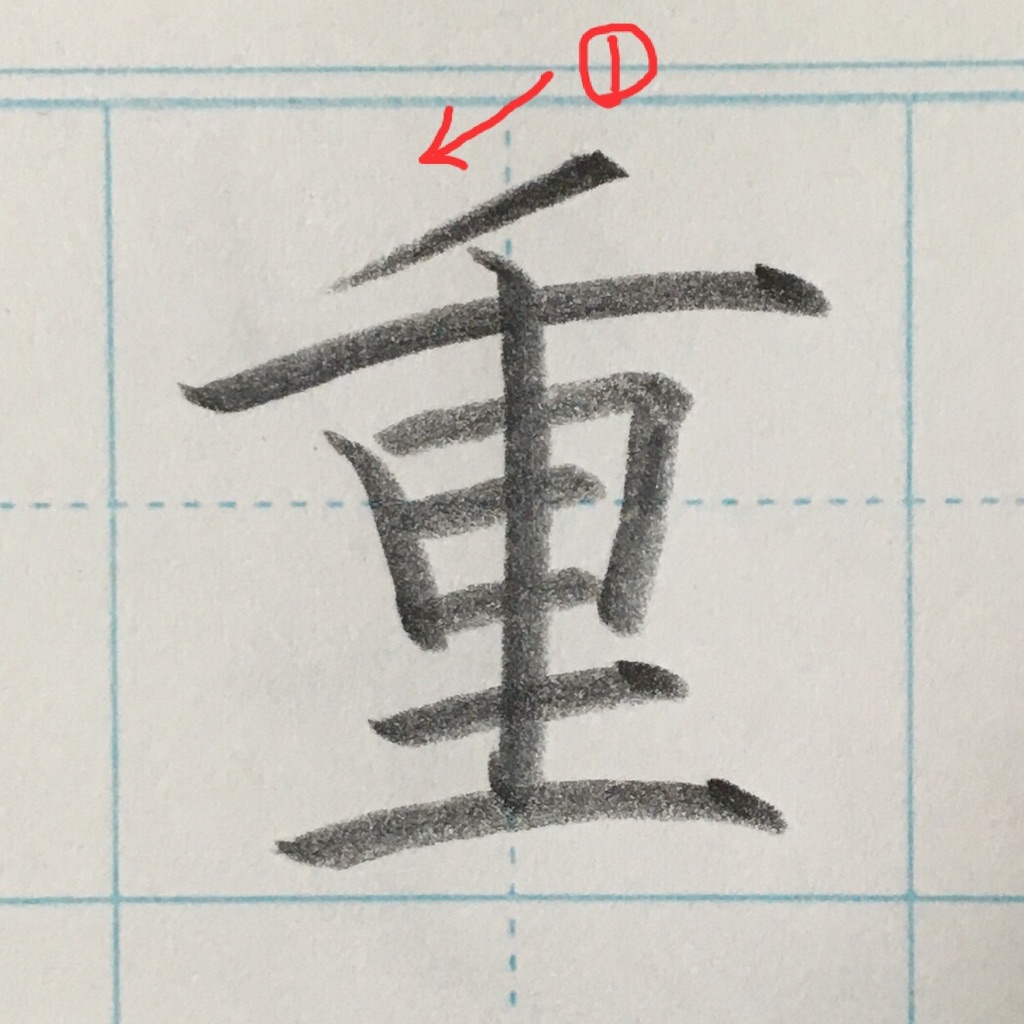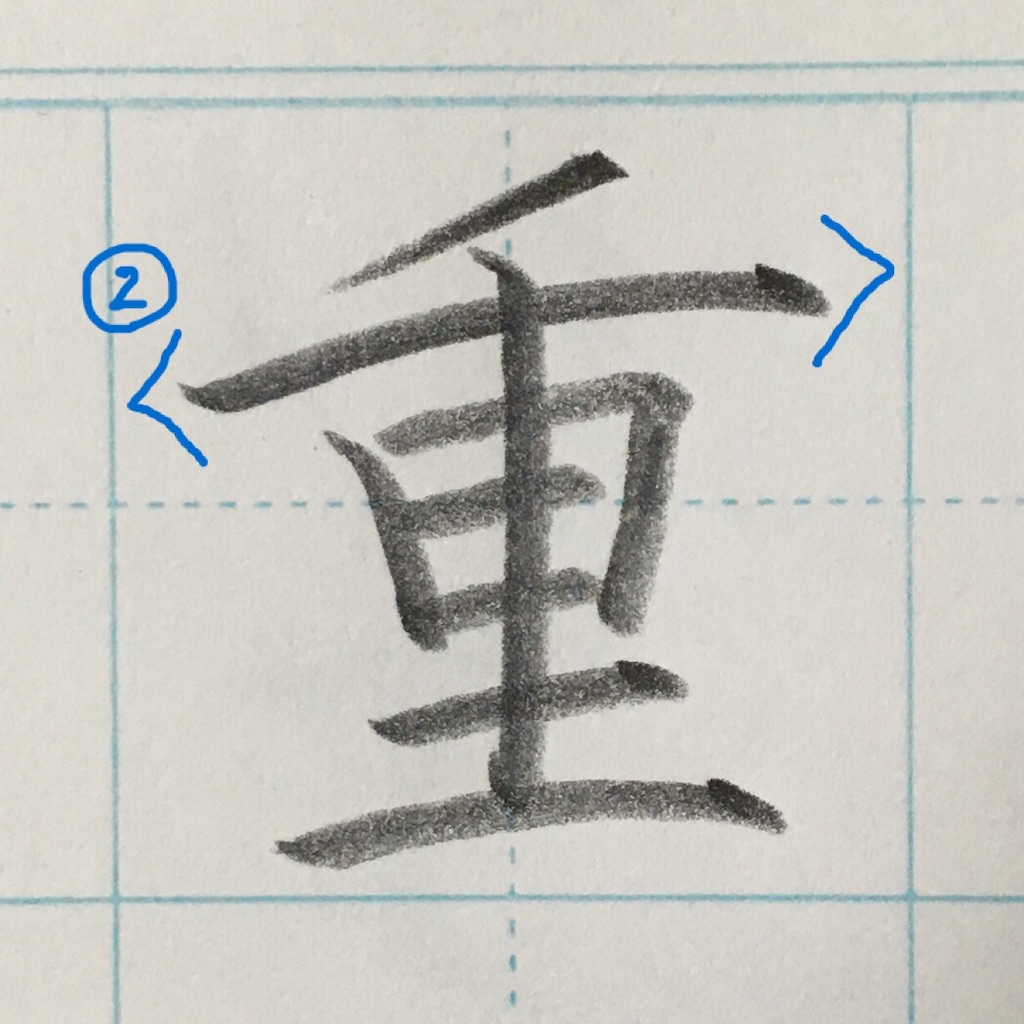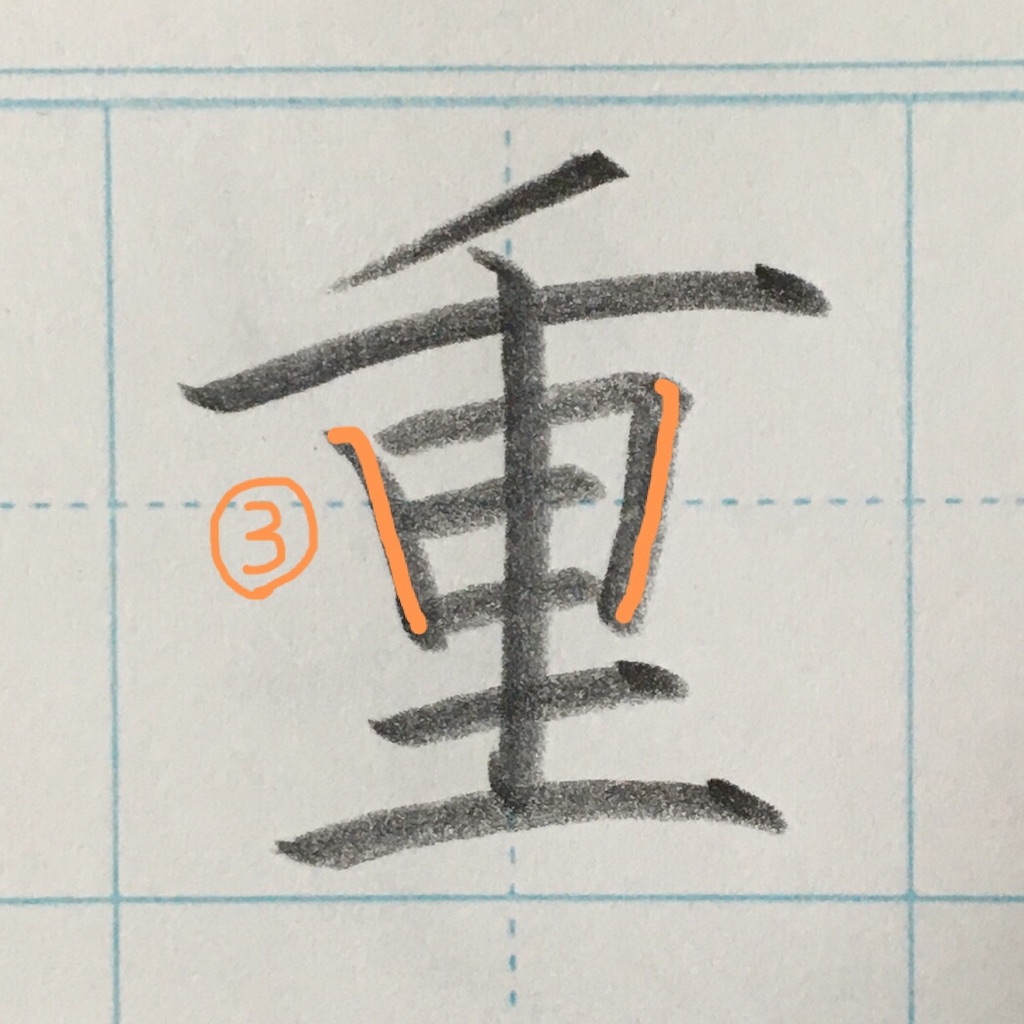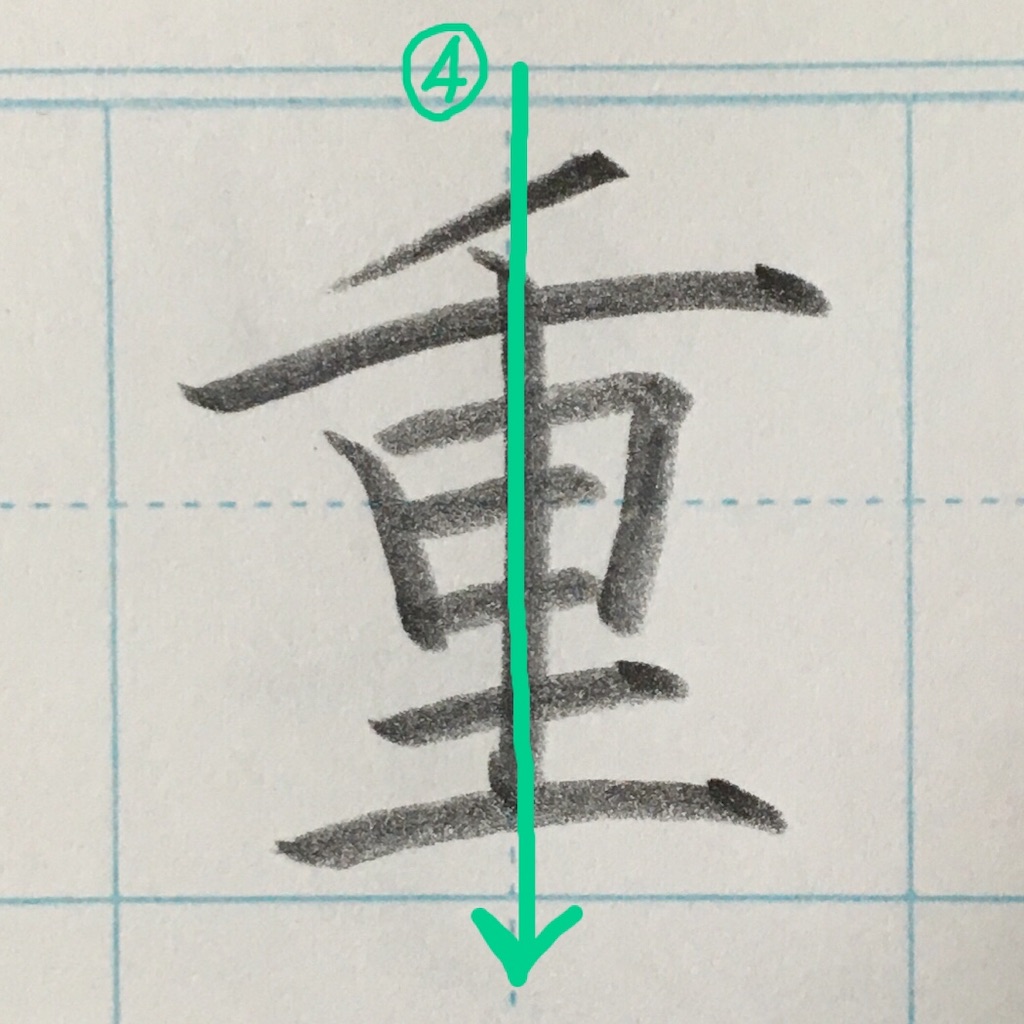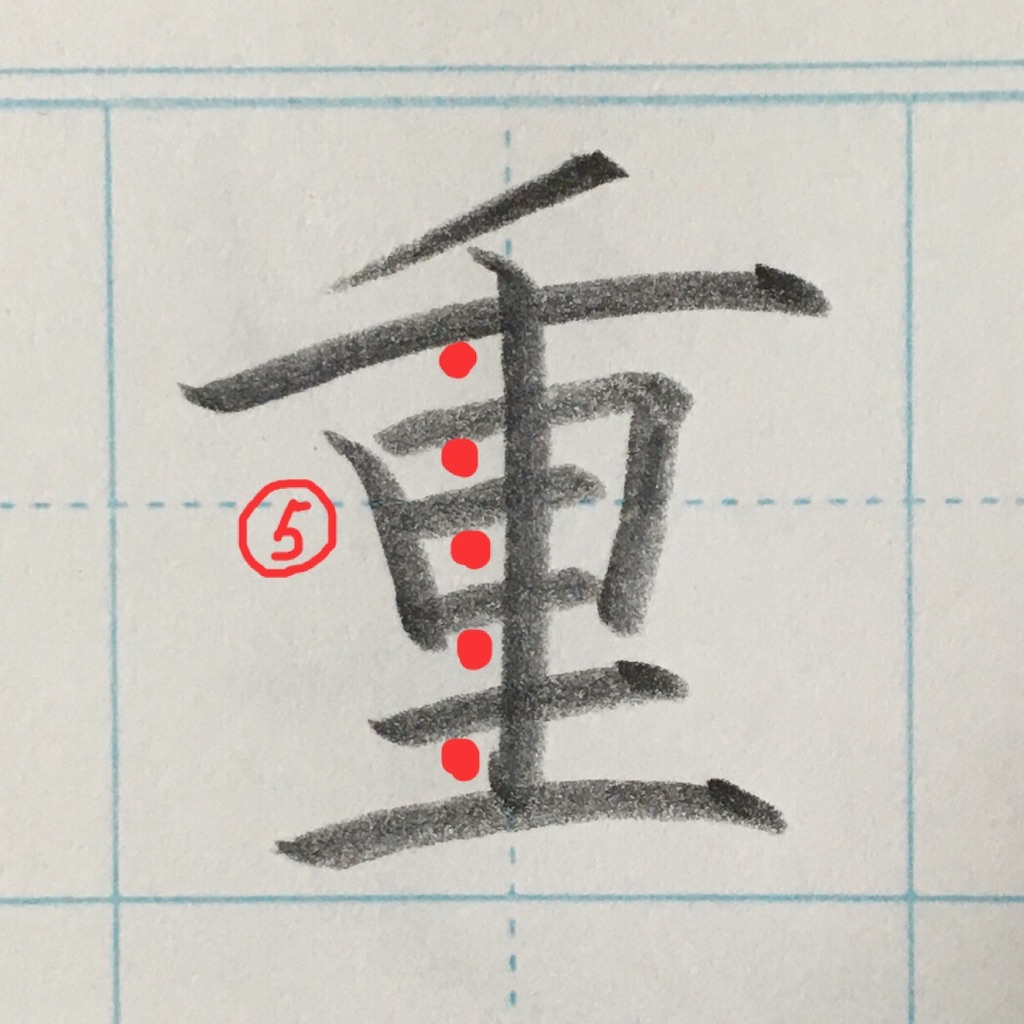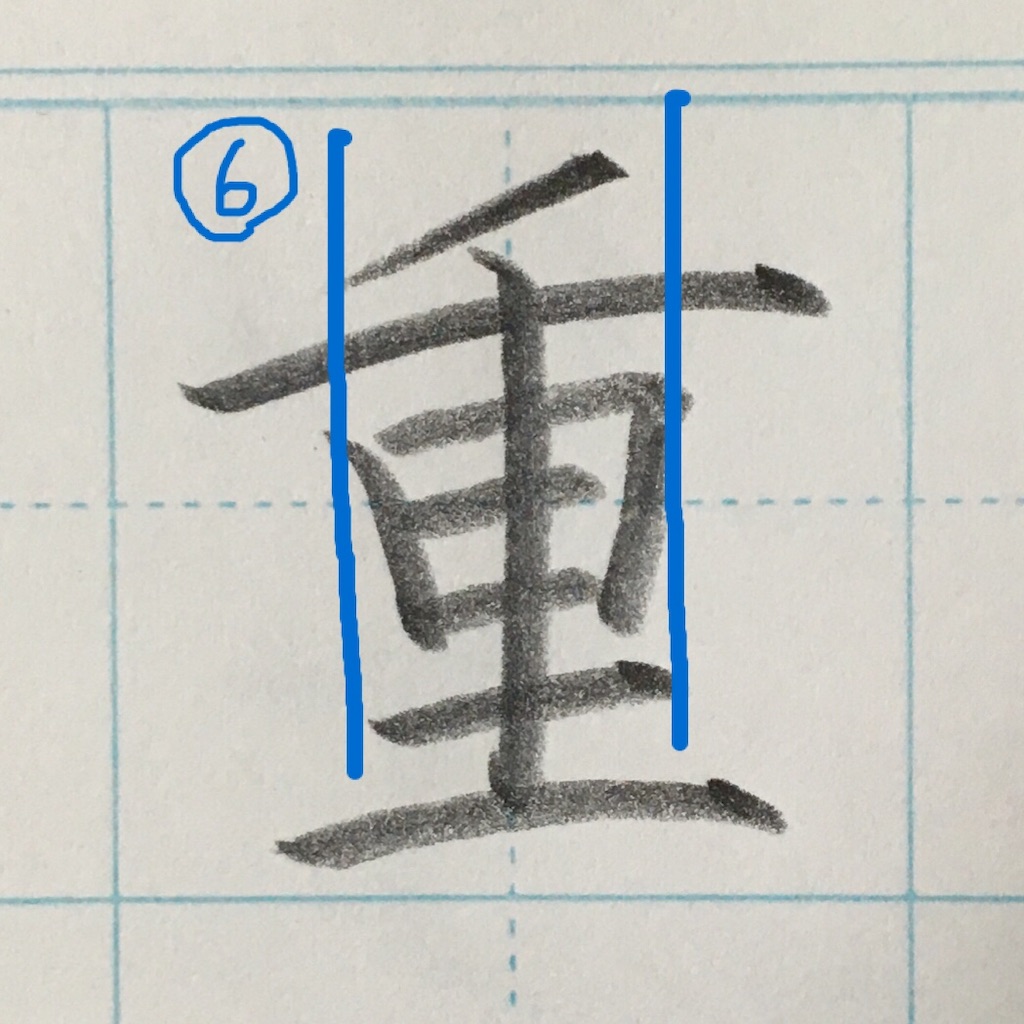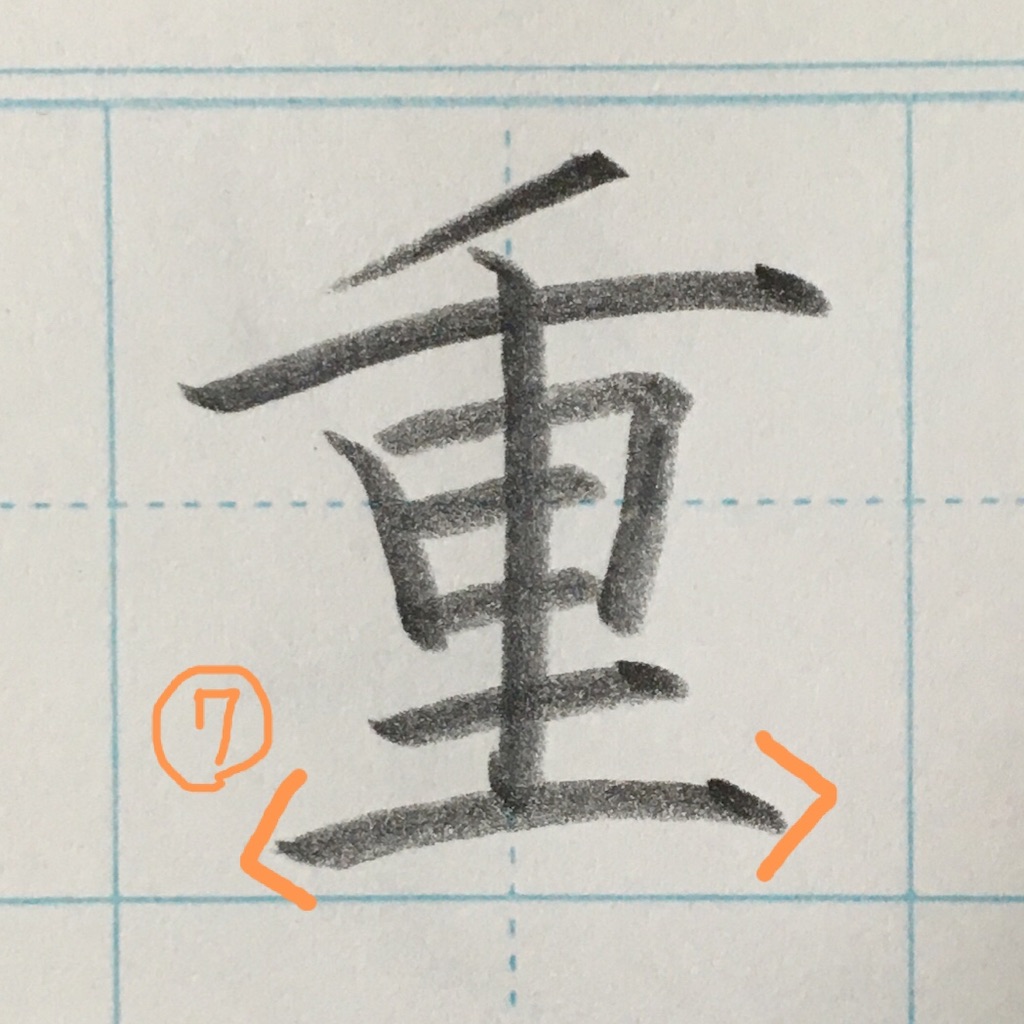
今回は「重」の書き方を解説します。
「重」のきれいな書き方。
「重」の書き方ポイント
➀1画目はできるだけ寝かせる。
(角度をつけると、2画目とぶつかってしまったり、
縦に長くなってしまうため。)
➁思い切って長く、強調する。
少し反ると◎。
☆中心に対して、左右の長さを等しく。
③同じ角度で内側に入れる。
☆中心に対して、左右の幅を等しく。
➃縦画は、中心にまっすぐ。
➄間隔を等しく。
(5画目の横画が、字の真ん中あたりにくるとGOOD!)
難しいですが、感覚が掴めるまで、慎重に丁寧に。
➅幅をだいたい揃える。
(長く強調する部分、
控えめな部分のメリハリを。)
⑦少し長くして、バランスを取る。
完成!